Opublikowany: 2022-03-18Twoje e-maile to zbiór zdań i słów. Słowa to zbiór znaków, a znaki to zbiór czcionek e-mail.
Dlatego musisz poświęcić tyle samo czasu i uwagi na czcionki w wiadomościach e-mail, co na pisanie tekstów — to podstawa Twoich wiadomości.
Jednak nie wszystkie czcionki są równe, zwłaszcza jeśli chodzi o program pocztowy. Najlepsze czcionki przyjazne dla e-maili sprawią, że Twoje kampanie będą błyszczeć, a niezbyt bezpieczne czcionki internetowe mogą spowodować awarię i spalenie Twoich projektów.
To może zabrzmieć trochę dramatycznie, ale to prawda. Każdy, kto wysłał wiadomość e-mail z nieobsługiwaną czcionką, będzie wiedział z doświadczenia.
Na szczęście nie musisz zgadywać, jeśli chodzi o wybór najlepszej czcionki e-mail dla swoich kampanii. Niezależnie od tego, czy projektujesz nowy biuletyn e-mailowy, czy dopracowujesz swój firmowy podpis e-mail, mamy sprawdzone czcionki, których potrzebujesz.
Co to są czcionki bezpieczne dla poczty e-mail?
Czcionki bezpieczne dla poczty e-mail są zwykle dostępne na najszerszej gamie komputerów, urządzeń i aplikacji. Możesz (ogólnie) oczekiwać, że te różne czcionki zostaną załadowane do skrzynek odbiorczych odbiorców, niezależnie od tego, czy używają oni Outlooka, Gmaila, Androida czy iPhone'a.
Jednak czcionki bezpieczne dla poczty e-mail nie są niezawodne. Zamiast tego dają one najlepszą szansę na zapobieganie zmianom czcionki.
Oprzyj się pokusie używania dowolnej czcionki, chcąc nie chcąc. Czemu? Ponieważ klienci poczty e-mail często nie wyświetlają określonych czcionek specjalnych i domyślnie dopasują do tekstu czcionkę zastępczą (prawdopodobnie jedną z czcionek bezpiecznych dla poczty e-mail wymienionych poniżej). Chociaż może to nie brzmieć jak problem, może mieć wpływ na ogólny projekt, układ, czytelność i jakość wiadomości e-mail.
Korzyści z używania odpowiedniej czcionki e-mail
Dlaczego wybór odpowiedniej czcionki e-maila ma znaczenie? Cieszymy się, że zapytałeś. Zamiast tylko trajkotać o projektowaniu i brandingu (które mają wiele zalet), spójrzmy na kilka popartych danymi powodów, dla których warto znaleźć odpowiednią czcionkę e-mail dla swoich kampanii:
- Zmaksymalizuj czas odbiorcy: użytkownicy poświęcają dwa razy więcej czasu na przeczytanie wymyślnych czcionek, ale spędzają średnio tylko 11 sekund na e-mail. Użyj odpowiedniej czcionki bezpiecznej dla poczty e-mail, a Twoi klienci mogą przeczytać 2 razy więcej wiadomości e-mail, zanim podejmą działanie lub przejdą do następnej.
- Zwiększ współczynnik konwersji: Click Laboratory zwiększyło konwersję formularzy aż o 133% , po prostu zmieniając rozmiar czcionki z 10-punktowej na 13-punktową i dodając odrobinę odstępu między wierszami — to wszystko.
- Wpływ na ocenę czytelnika: niektóre czcionki wpływają na to, jak ludzie W tym badaniu czcionka Baskerville zwiększyła liczbę osób zgadzających się ze stwierdzeniem o 1,5%. To może nie brzmieć znacząco, ale 1,5% może mieć ogromny wpływ na Twój wynik finansowy.
- Popraw czytelność: większość ludzi nie ma różnych doświadczeń z szybkością lub retencją podczas czytania czcionek szeryfowych i bezszeryfowych. Jednak dzieci, osoby starsze, osoby z ograniczonym wzrokiem i osoby z dysleksją lepiej czytają czcionki bezszeryfowe .
8 najlepszych czcionek przyjaznych dla poczty e-mail
Stwierdziliśmy, że następujące czcionki są najbardziej przyjazne dla poczty e-mail i bezpieczne w Internecie. Użyj tych czcionek, aby zwiększyć szanse na prawidłowe renderowanie czcionek w wiadomościach e-mail z odbiorcami:
- Arial
- Courier New
- Gruzja
- Helvetica
- Lucida Sans
- Tahoma
- Czcionka Times New Roman
- Trebusz MS
1. Arial
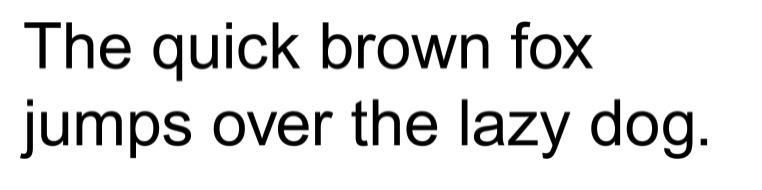
Arial to jedna z bardziej współczesnych opcji czcionek bezszeryfowych, które są bezpieczne dla poczty e-mail. Dzięki niemu znajdziesz miękkie i pełne krzywizny, które nadają mu znacznie bardziej nowoczesny wygląd. Arial to doskonała czcionka do kopiowania treści lub nagłówków w kampaniach e-mailowych.
2. Kurier Nowy
Courier New ma wygląd przypominający maszynę do pisania z łatwymi do odczytania szeryfami. Nie ma też nowoczesnego wyglądu i stylu, dzięki czemu jest bardziej odpowiedni dla scenariuszy filmowych i rękopisów niż e-maili — ale dla każdego z nich osobno.
3. Gruzja
Georgia to klasyczna czcionka szeryfowa firmy Microsoft, często używana w gazetach i czasopismach. Nadaje autorytatywny (i formalny) wygląd Twoim e-mailom i jest doskonałą opcją dla czytelności, jeśli treść zawiera więcej słów.
4. Helvetica
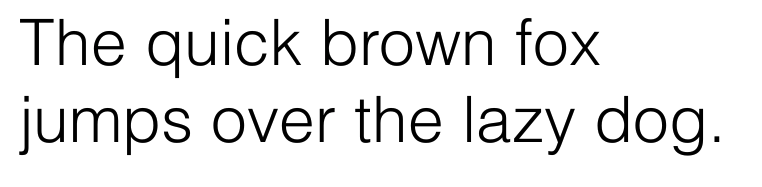
Helvetica jest prawdopodobnie najpopularniejszą czcionką cyfrową. Nie jest świetny do kopiowania treści, ale ma klasyczny cios, gdy jest używany w tytułach, nazwach marek, sloganach, sloganach i nagłówkach. Helvetica nie pomoże Twojej marce się wyróżnić (wszyscy jej używają), ale jest uosobieniem „bezpiecznego” czegoś więcej niż tylko przyjaznej poczty e-mail.
5. Lucida bez Unicode
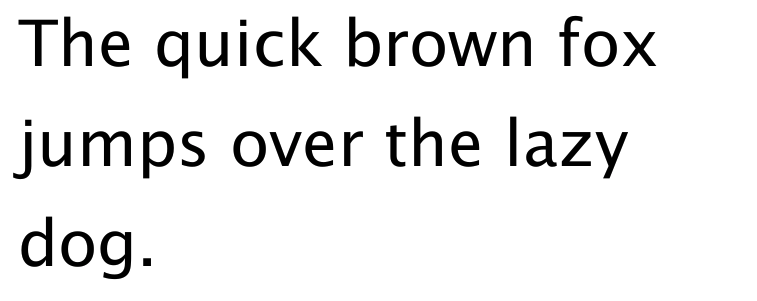
Lucida Sans Unicode to prosty i czytelny wariant rodziny czcionek Lucida bezszeryfowy. Nie ma też odmian pogrubienia ani kursywy.
6. Tahoma
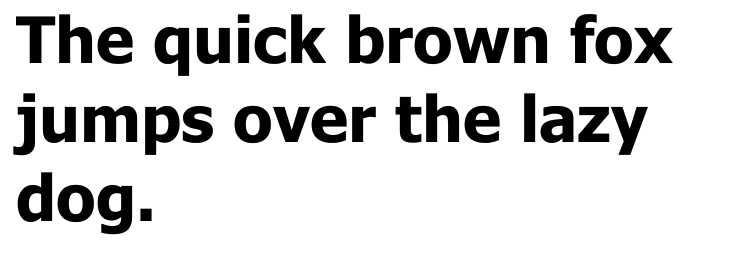
Tahoma, zaprojektowana przez Microsoft czcionka, która pomaga w wyświetlaniu na ekranie małego tekstu w oknach dialogowych i menu, dobrze przekłada się na mały i ograniczony charakter wiadomości e-mail.
7. Times New Roman
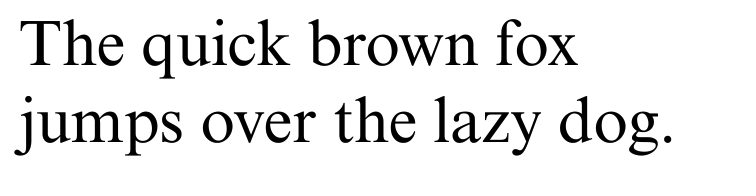
Czcionka Times New Roman. Jaka lista byłaby kompletna bez tego? Ta wypróbowana i bezpieczna czcionka e-mail jest bezpieczna w użyciu w dowolnym miejscu. Nie jest to współczesna czcionka (istnieje od prawie 100 lat), ale zajmuje mało miejsca, jest czytelna i znajoma.
8. Trebusz MS
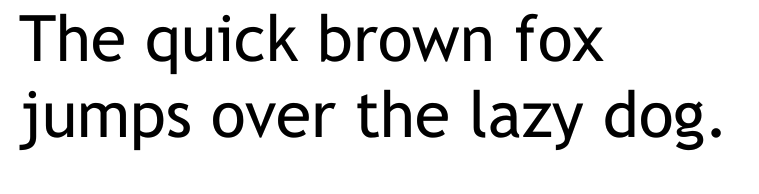
Trebuchet MS to jedna z odważniejszych, przyjaznych cyfrowo czcionek o niepowtarzalnym wyglądzie. Podczas gdy niektóre postacie wydają się klasyczne i typowe, inne stają się wręcz kreatywne (patrz „g”).
Co to jest czcionka e-mail bezpieczna w Internecie?
Czcionki bezpieczne dla poczty e-mail i czcionki internetowe to nie to samo. Czcionki bezpieczne w Internecie istnieją w sieci (zgadłeś) — co oznacza, że nie znajdziesz ich natywnie zawartych w systemach operacyjnych, urządzeniach, oprogramowaniu lub aplikacjach.
Te czcionki istnieją tylko w trybie online i można je dodawać do komunikacji i aplikacji za pomocą wtyczek i fragmentów kodu. Większość klientów poczty e-mail obsługuje kilka bezpiecznych w Internecie czcionek e-mail, ale to nie znaczy, że wszystkie z nich się pokrywają.
Na przykład Gmail obsługuje czcionki internetowe Open Sans i Roboto, ale Outlook i Apple Mail nie. Jednak każdy klient poczty e-mail ma domyślną czcionkę, którą można przywrócić, jeśli nie obsługuje czcionki internetowej. Tu jest kilka:
- Gmail: Arial
- Poczta Apple: Helvetica
- Perspektywy: Kalifornia
Trudno jest zaprojektować jedną wiadomość e-mail dla Helvetica, drugą dla Roboto i inną dla Calibri — dlatego łatwiej jest używać czcionek bezpiecznych dla poczty e-mail, które działają uniwersalnie w większości klientów poczty e-mail. Pamiętaj, że możesz zmienić czcionkę zastępczą.
11 niestandardowych czcionek e-mail w formacie HTML
Jeśli zamierzasz używać czcionki bezpiecznej dla poczty e-mail zamiast czcionki bezpiecznej dla poczty e-mail, zalecamy wybranie (i przetestowanie) opcji zastępczej czcionki, takiej jak jedna z poniższych. Przeanalizuj, jak to wygląda z preferowanymi czcionkami i opcjami zastępczymi na różnych urządzeniach i w klientach poczty e-mail, aby upewnić się, że wygląda to odpowiednio i nie psuje formatu.
1. Raway
Raleway to czcionka bezszeryfowa z cienkimi, grubymi liniami i dużymi odstępami między literami, co zapewnia łatwe czytanie bez marnowania miejsca na stronie.
2. Roboty
Roboto używa przyjaznych i otwartych krzywych o naturalnej szerokości, aby stworzyć czcionkę przyjazną dla oczu. Jest to również domyślna czcionka w Androidzie, Google Play, YouTube, Mapach Google i Grafice Google.
3. Otwórz Sans
Open Sans to czcionka zoptymalizowana pod kątem drukowania, Internetu i interfejsów mobilnych dzięki neutralnemu, przyjaznemu wyglądowi. Pionowa natura i odstępy między literami stawiają na pierwszym miejscu czytelność.
4. Poppiny
Poppins ma przejrzysty wygląd i styl czcionki, dzięki czemu idealnie nadaje się do nagłówków, podtytułów i wyróżniających się kopii akapitów. Zapewnia doskonałą równowagę między zabawą a profesjonalizmem.
5. Oswald
Oswald to zwarta, skondensowana czcionka, która pozwala wcisnąć więcej znaków bez poświęcania czytelności. Użyj Oswalda w nagłówkach, aby zapakować cios bez rozciągania tekstu zbyt daleko w pionie lub poziomie.
6. Ubuntu
Czcionka Ubuntu charakteryzuje się współczesnym stylem i niepowtarzalną atmosferą, równoważącą uderzający design z profesjonalnymi zastosowaniami.
7. Merriweather
Merriweather to czcionka szeryfowa typu open source przeznaczona do odczytu cyfrowego. Znaki rozciągają się wysoko, ale pozostają stosunkowo małe, aby zwiększyć czytelność bez marnowania miejsca.
8. Rubik
Rubik wykorzystuje lekko zaokrąglone rogi i niski kontrast. Uzyskaj bezpłatny dostęp do tego kroju pisma typu open source w Google Fonts.
9. Ruchome piaski
Quicksand, pierwotnie zaprojektowany do celów wyświetlania, to czcionka bezszeryfowa, która nadal dobrze sprawdza się również w małych rozmiarach druku. Świetnie sprawdza się w przypadku tekstu podstawowego w wiadomościach e-mail.
10. Tlen
Oxygen to bezpieczna w Internecie czcionka przeznaczona do użytku w przeglądarkach internetowych, komputerach stacjonarnych i urządzeniach mobilnych. Świetnie łączy się z Oswaldem i Quicksandem.
11. Lato
Lato to dobrze zbudowana czcionka z 18 stylami i grubościami oraz ponad 3000 glifów na styl. Zawiera półzaokrąglone krawędzie i przystępne ciepło, dzięki czemu jest jedną z najpopularniejszych czcionek Google.
Najlepsze czcionki e-mail do przypadków użycia
Nie musisz ograniczać się do jednej czcionki wiadomości e-mail dla wszystkich wiadomości e-mail — niektóre z nich działają lepiej jako nagłówki, treść lub podpisy. Poniżej wymieniliśmy najlepsze czcionki dla kilku przypadków użycia poczty e-mail.
Najlepsze czcionki do podpisów e-mail
W podpisie e-mail zalecamy bezpieczną czcionkę internetową z rezerwową czcionką bezpieczną dla poczty e-mail. Ponieważ prawdopodobnie będzie tak samo w większości e-maili, możesz poświęcić czas na optymalizację wersji bezpiecznej w Internecie i opcji awaryjnych, aby zapewnić dopracowany, spójny wygląd.
Poniższe bezpieczne internetowe czcionki e-mail są naszymi zaleceniami dotyczącymi podpisów w wiadomościach e-mail:
- Poppins
- Otwórz Sans
- Roboto
- Oswald
- Lato
Jako opcje awaryjne zalecamy:
- Arial
- Helvetica
- Tahoma
Najlepsze profesjonalne czcionki e-mail dla biznesu
Niektóre czcionki są zabawne, a inne bardziej profesjonalne — a niektóre unikalne zapewniają równowagę między osiąganiem obu. Jednak jeśli chodzi o profesjonalne czcionki e-mail dla biznesu, zalecamy wybór czcionek, które wykazują zaufanie i klasę:
- Ubuntu
- Poppins
- Arial
- Helvetica
- Gruzja
Najlepsze czcionki do biuletynów e-mail
Biuletyny e-mailowe często muszą zawierać mnóstwo świetnych treści na niewielkiej przestrzeni. Jeśli to jest problem, z którym borykasz się podczas projektowania kampanii, zalecamy następujące czcionki do biuletynów e-mail:
- Raleway
- Oswald
- Tahoma
Najlepsze czcionki do kampanii e-mail marketingowych
Twoje kampanie e-mail marketingu powinny używać wielu czcionek do oddzielania (i odróżniania) nagłówków od treści. Następujące czcionki dobrze pasują do kampanii e-mail marketingowych:
- Raleway i Merriweather
- Open Sans i Times New Roman
- Lato i Merriweather
- Roboto i Lato
Najlepsze czcionki Gmaila
Gmail jest najpopularniejszą skrzynką odbiorczą poczty e-mail z 1,8 miliarda aktywnych użytkowników , i istnieje szansa (w zależności od Twojej grupy demograficznej), że zdecydowana większość Twoich odbiorców korzysta z tego klienta poczty e-mail. W takim przypadku użyj bezpiecznej w Internecie czcionki zoptymalizowanej pod kątem Gmaila z opcjami awaryjnymi na wypadek, gdyby adresaci korzystali z innych skrzynek odbiorczych. Polecamy:
- Arial
- Otwórz Sans
- Roboto
Jak zoptymalizować czcionki do poczty e-mail
Wybór czcionki nie jest łatwy, ale wierzymy w Ciebie. Gdy już dokonasz wyboru, nadszedł czas na optymalizację czcionek lub kampanii e-mailowych. Obejmuje to odpowiednie ich wykorzystanie, zwiększenie czytelności i poprawę obsługi klienta.
1. Zachowaj prostotę
Pamiętaj, że celem twojej czcionki nie jest wywoływanie „ochów” i „achów” — chodzi o to, aby odbiorcy przeczytali Twoje e-maile i podjęli działania. Zachowaj prostotę i markę.
Zawsze poświęcaj kreatywność, a nawet markę, aby poprawić czytelność, zrozumienie i wrażenia użytkownika. Twórcy marki mogą potrząsnąć pięścią za to, że to powiedziałem, ale to zimna, twarda prawda.
Jednak złotym środkiem jest połączenie kreatywności i doświadczenia użytkownika, aby stworzyć najwyższej klasy e-maile, które wzmocnią Twoją markę i zaangażowanie.
2. Nie umieszczaj swojego e-maila w obrazach
Jednym ze sposobów, aby czcionki (dowolne) wyświetlały się poprawnie w wiadomości e-mail, jest dodanie ich do osadzonych obrazów — ale to duży e-mail, nie. Chociaż może to ułatwić zespołowi kreatywnemu wysyłanie spójnych kampanii e-mail dotyczących marki (wszystkie bez kodowania), wysyłanie e-maili zawierających tylko obrazy jest złą praktyką. Oto dlaczego z Litmusa :
- Twoi subskrybenci mogą mieć wyłączone obrazy.
- Odbiorcy niedowidzący mogą nie być w stanie odczytać wiadomości e-mail.
- Tekstu e-maila nie będzie można przeszukiwać, co utrudni użytkownikom późniejsze odnalezienie e-maila.
- E-maile wypełnione obrazami będą ładowały się powoli (lub wcale).
- Tworzenie responsywnych obrazów, które dobrze prezentują się na każdym urządzeniu, to nie lada wyzwanie.
- Tryb ciemny może robić dziwne rzeczy z obrazami, na przykład odwracać kolory.
- Kopiowanie zmian trwa wiecznie — zamiast tylko poprawiać błędnie napisane słowo, musisz edytować, pobierać i ponownie przesyłać nowy obraz.
3. Wybierz czcionkę zastępczą
Wybierz i przetestuj czcionki zapasowe do kampanii e-mail, zwłaszcza jeśli używasz czcionek internetowych zamiast czcionek bezpiecznych dla poczty e-mail. Każdy klient poczty e-mail ma domyślne opcje awaryjne, ale możesz je zastąpić swoim wyborem.
Jeśli wybierzesz niewłaściwą czcionkę zastępczą, projekt wiadomości e-mail może się zwinąć i utracić pierwotne formatowanie. Znajdź czcionki o podobnych wysokościach, szeryfach (lub bezszeryfowych) i odstępach między literami, aby zapobiec awariom i wypaleniu projektu.
4. Nie zapomnij o rozmiarze czcionki
Rozmiar czcionki może spowodować lub przerwać kampanię e-mailową. Zbyt duży i nie zmieścisz całego potrzebnego tekstu. Zbyt mały, a subskrybenci będą mieli trudności z jego przeczytaniem.
Email on Acid zaleca używanie czcionki o rozmiarze co najmniej 14 pikseli. Jednak niektórzy sprzedawcy poczty e-mail zwiększą rozmiar czcionki globalnie lub w sposób responsywny na urządzeniach mobilnych do 16 lub 18 pikseli, aby poprawić czytelność.
5. Przetestuj swoje e-maile przed wysłaniem
Przetestuj swoje e-maile przed ich wysłaniem, aby upewnić się, że będą wyglądać dobrze na klientach, przeglądarkach i urządzeniach (iOS i Android). Jednak zamiast tworzyć konta w Gmailu i Outlooku oraz wysyłać sobie testowe wiadomości e-mail w celu sprawdzenia na komputerze i urządzeniu mobilnym, skorzystaj z naszego narzędzia do testowania poczty e-mail .
Jest zintegrowany z naszym narzędziem do tworzenia wiadomości e-mail, co ułatwia testowanie podczas projektowania, zamiast czekać do końca. Testowanie poczty e-mail Twilio SendGrid przeanalizuje również Twój e-mail w celu znalezienia uszkodzonych linków, problemów z wyświetlaniem, a nawet treści spamerskich.
6. Ogranicz czcionki e-maili
Nie chcesz zaśmiecać swoich e-maili zbyt wieloma czcionkami — może to rozpraszać i rozpraszać. Zamiast tego zalecamy ograniczenie się do 2 czcionek. I to nie tylko 2 czcionki — znajdź czcionki, które dobrze ze sobą współpracują.
Równie ważna jest spójność ze sposobem, w jaki używasz czcionek w wiadomości e-mail. Na przykład, jeśli używasz jednej czcionki w nagłówku, a drugiej w treści, nie przerzucaj między nimi w połowie wiadomości e-mail.
7. Zwróć uwagę na odstępy między wierszami i literami
Niezależnie od wybranej czcionki, podczas projektowania wiadomości e-mail warto zwrócić uwagę na odstępy między wierszami i literami. Zbyt mało miejsca lub zbyt duże odstępy między literami utrudnią czytanie.
Zalecamy dodanie odrobiny odstępów między literami dla całego tekstu pisanego wielkimi literami. Wielkie litery mogą czasem przenikać do siebie, a odrobina odstępu może zajść daleko. Rozważ również dodanie odstępów między literami w przypadku tekstu mniejszego niż zwykle. Pomaga to zachować niewielki rozmiar bez utraty czytelności.